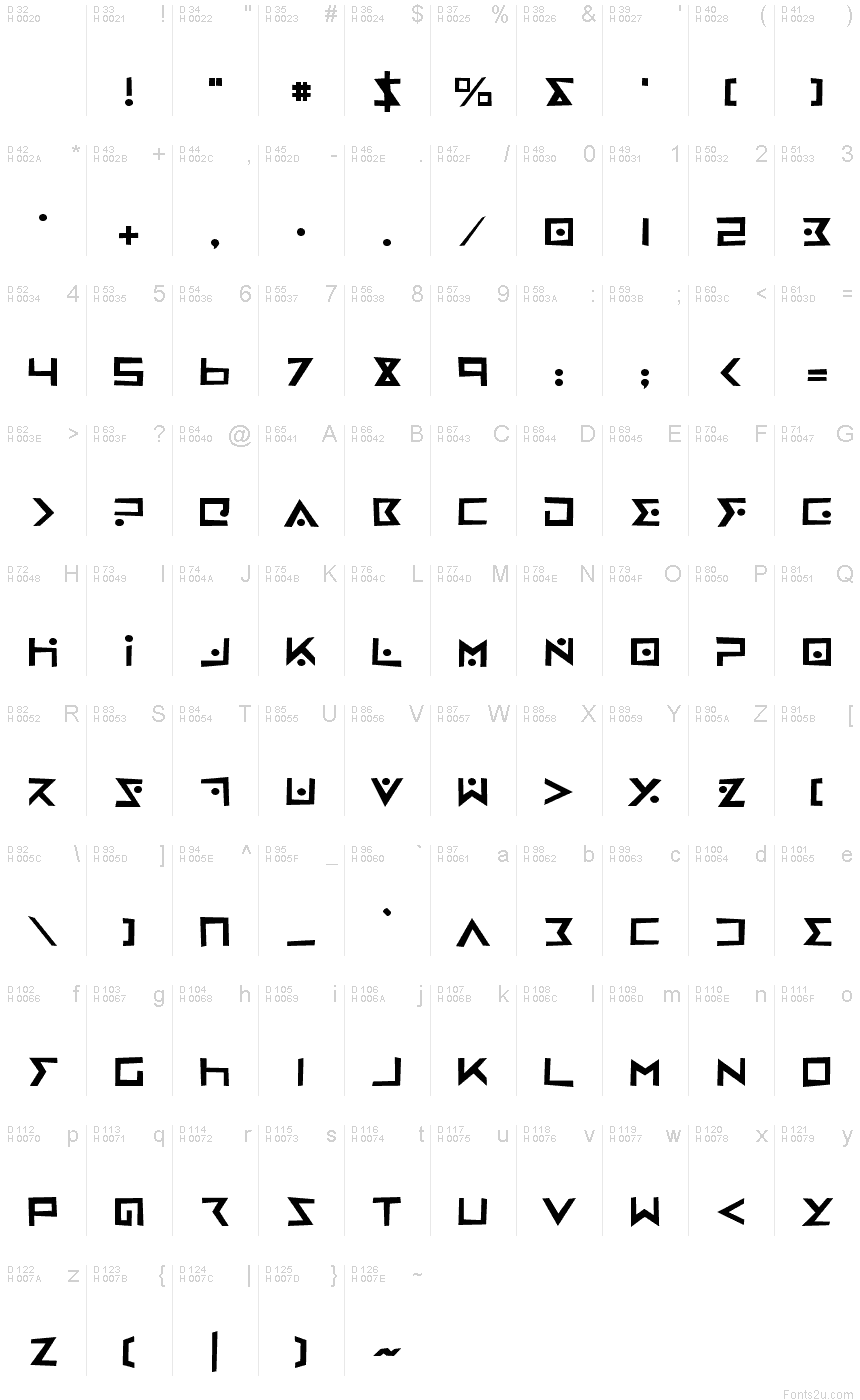
Iron Cobra Rough od Iconian Fonts to darmowy, techno-displayowy krój pisma o ostrym, maszynowym charakterze. Litery oparte są na wyrazistych skosach, szerokich formach i nieco nieregularnej geometrii, dzięki czemu klimat sci-fi nie wydaje się zbyt sterylny.
Świetnie sprawdza się w logotypach gier, tytułach na plakatach, okładkach albumów, miniaturach streamingowych czy oprawie eventów, gdzie potrzeba kompaktowego napisu z syntetycznym pazurem. Jako darmowy font, doskonale nadaje się również do napisów tytułowych i krótkich nagłówków w stylu interfejsu, ponieważ kwadratowe kształty i ścięte rogi nadają nawet krótkim tekstom dynamiczny, inżynieryjny rytm.
Iron Cobra Rough